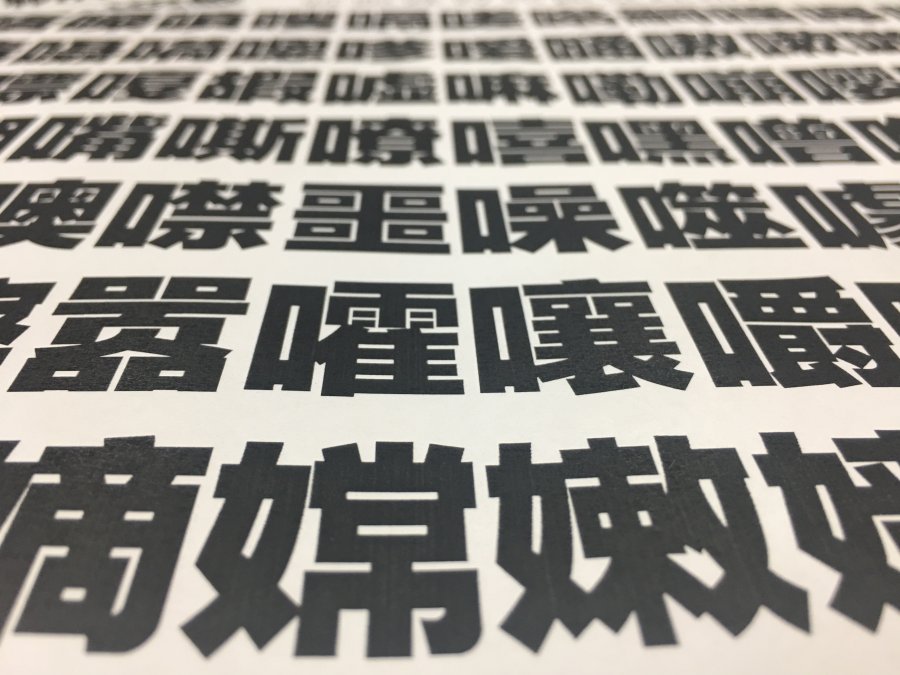
思源黑体字体可以说是支持简体、繁体,还有日文、韩文以及希腊语、拉丁语、西里尔,有着将近五十万的字。而打造这么一个庞大的字体家族,则是中国和韩国,再加上5家企业连同一起设计的,这款字体的创造工程前所未有。思源黑体中文,是联合了中日韩五家公司联合开发设计而成的一系列字体。
思源黑体中文的风格是在传统和现代之间,设计的初衷是广泛使用在计算机上,包括手机平板、电脑左面或者页面浏览以及电子书。目前主要有7个字重:从ExtraLight,Light, DemiLight,Regular,Medium,Bold到Black。有消费者就认为,这种字体将会替代微软字体。